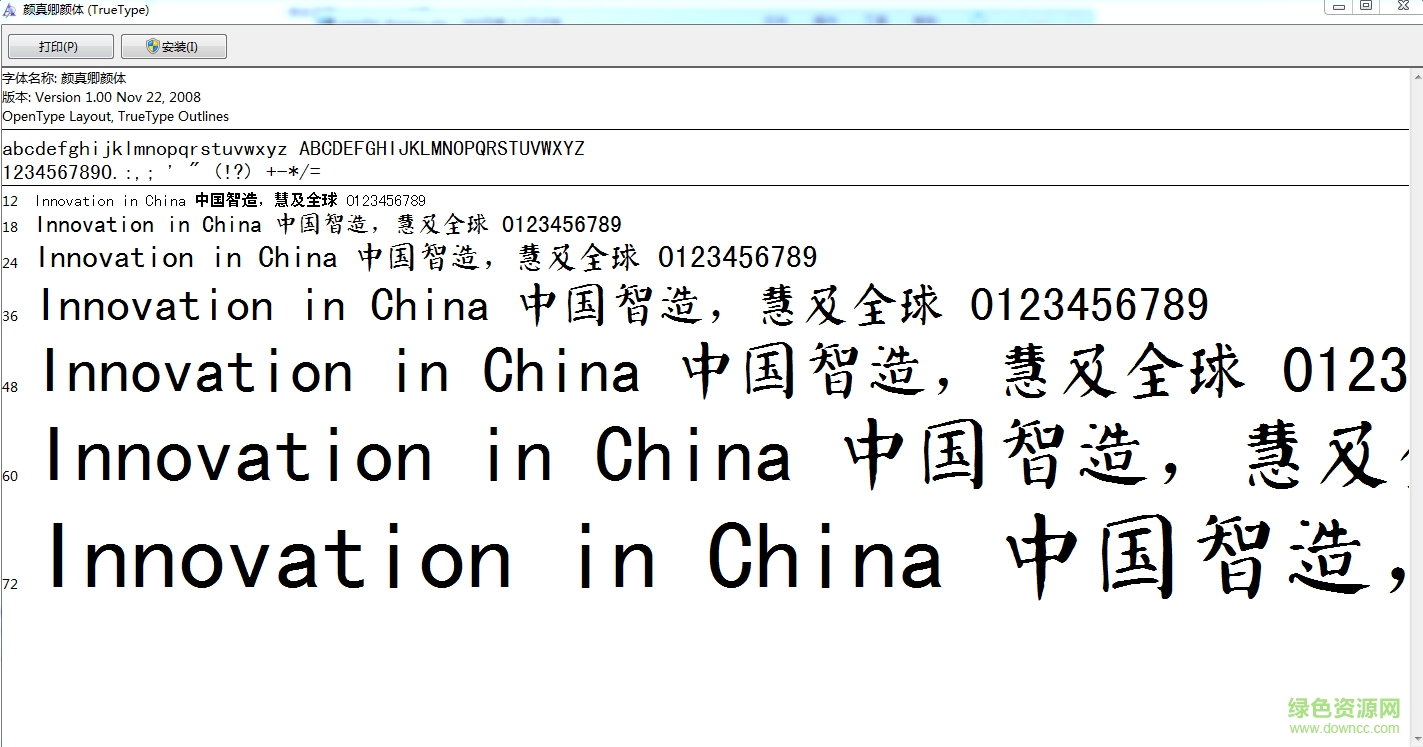
顏真卿顏體書法字體是出自著名書法家顏真卿的字體,筆畫飛揚(yáng),遒勁有力,極具美感,該字體為通用的TTF格式,有需要的朋友可以免費(fèi)下載收藏。
顏真卿書法精妙,擅長行、楷,創(chuàng)“顏體”楷書,與趙孟頫、柳公權(quán)、歐陽詢并稱為“楷書四大家”。又與柳公權(quán)并稱“顏柳”,被稱為“顏筋柳骨”。又善詩文,有《韻海鏡源》、《禮樂集》、《吳興集》、《廬陵集》、《臨川集》,均佚。宋人輯有《顏魯公集》。